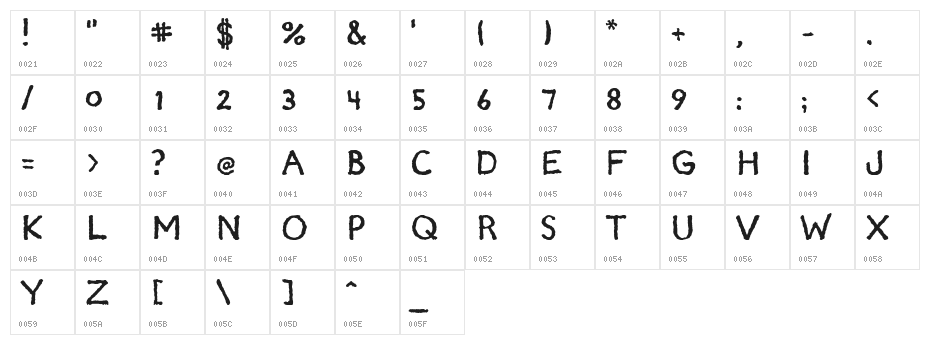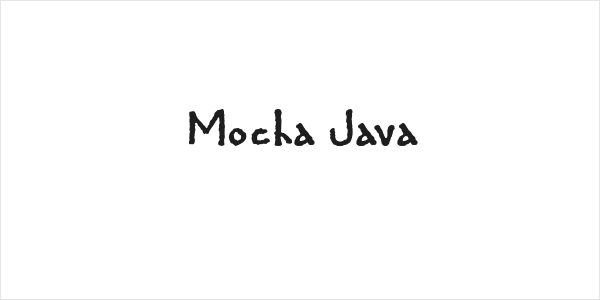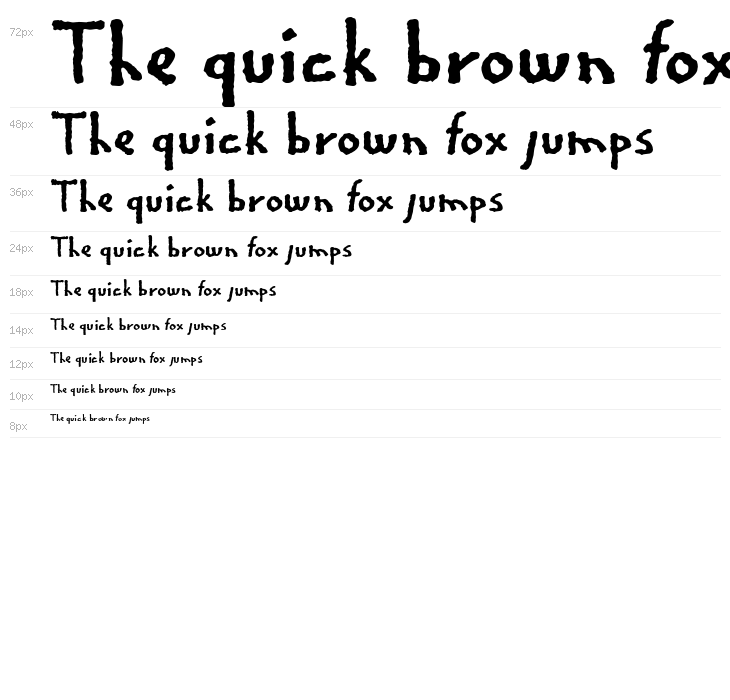
Mocha Java Font
| Stile generale | Casual, Playful |
| Caso d'uso | Headlines, Informal text, Creative projects |
| Progetti proposti | Ideal for greeting cards, children's books, casual branding, and creative projects that require a personal touch. |